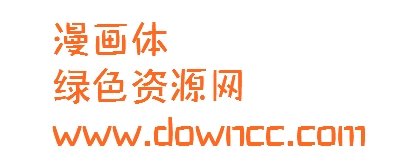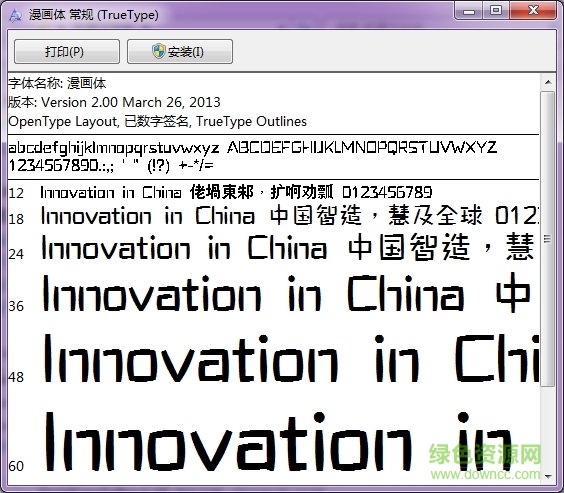
漫畫體是一款支持犯賤輸入的常見藝術(shù)字體,字體生動別致,自己清晰有型,在很多漫畫圖像中常有出現(xiàn),歡迎大家來綠色資源網(wǎng)免費(fèi)下載!
漫畫體是從手機(jī)字體中提取出來的卡通字體,字體粗黑,線條隨意,字形活潑生動,個(gè)性又實(shí)用,給人活潑、可愛、孩子氣般的感覺,可以廣泛運(yùn)用于平面設(shè)計(jì)、海報(bào)設(shè)計(jì)等場合。
動畫漫畫的Logo和字體一直都是表現(xiàn)作品風(fēng)格的標(biāo)志,一般都比較生動活潑,具有鮮明的個(gè)性,此款字體適用于兒童讀物、報(bào)刊雜志標(biāo)題、廣告設(shè)計(jì)等視覺環(huán)境,有著極強(qiáng)的應(yīng)用空間。